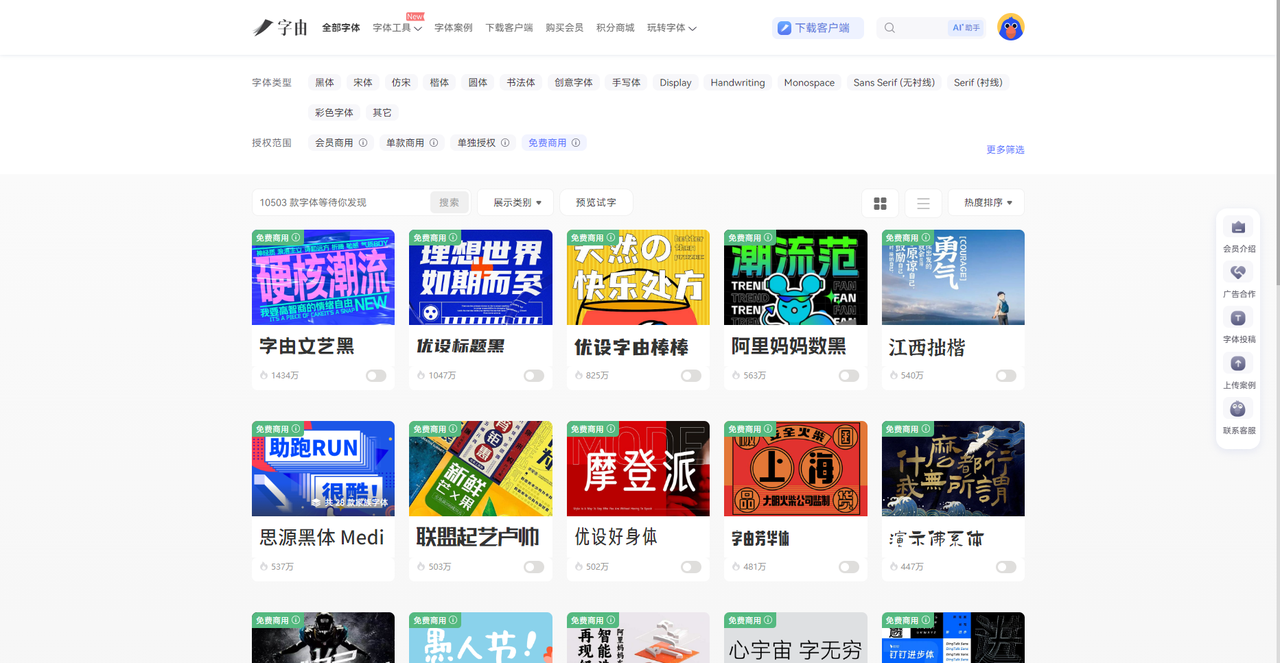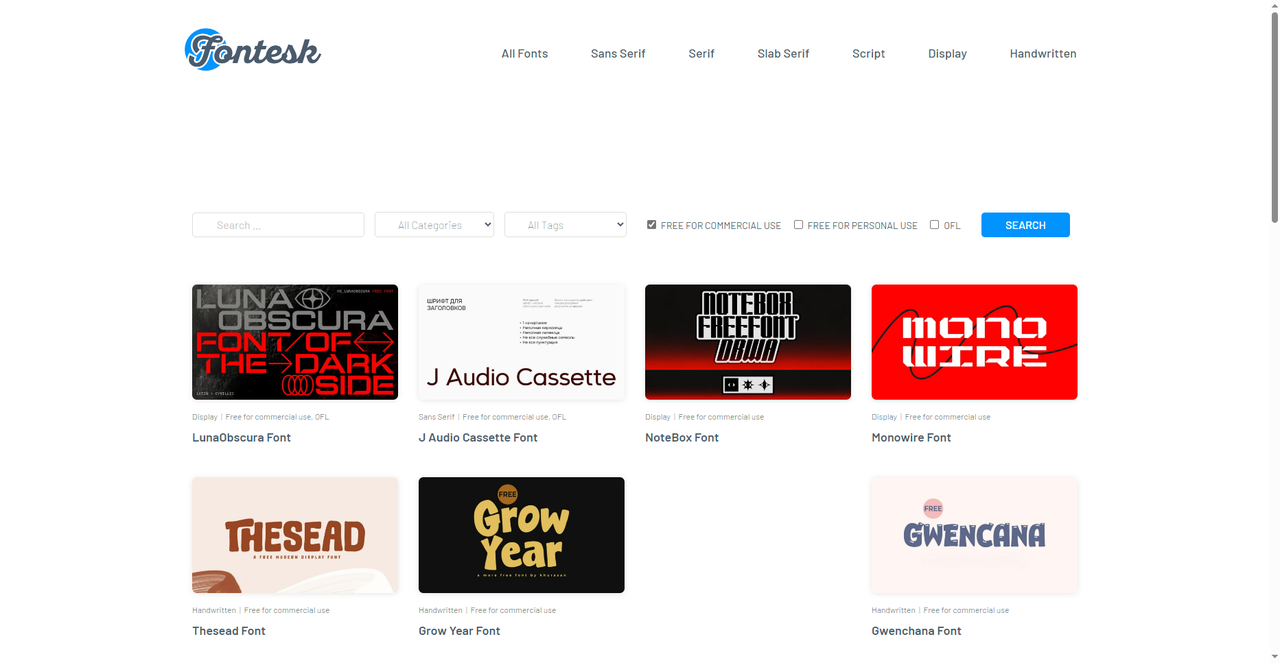
设计师必备!5个可免费商用字体下载网站推荐
每次做设计,总有一瞬间特别纠结:字体选好了,心里却打鼓——这字体到底能不能商用?要不要再查一遍?查吧,怕麻烦;不查吧,又怕出事。最后往往还是妥协,换回系统自带的那几款。明明有那么多好看的字体,就因为“不确定”,不敢用。后来我才发现,其实不是没有好字体,而是没找对地方。那么今天我就会把一些能够明确可以免费商用的字体网站分享给大家,让大家实现用字自由!
很多人用字由,只看到它字体多,却没发现它最好用的是筛选功能。字由收录了超过10500 款字体,其中3585 款是免费可商用的。但如果你不会筛,就会觉得“怎么这么多”。其实掌握下面3 步,你就能在字由里精准定位到想要的那一款。下面我会教大家具体的步骤:
- 第一步:先选授权范围
打开字由客户端或网页版,点进“全部字体”,第一个要看的就是“授权范围”。直接点“免费商用”,系统立刻从一万多款字体里筛出3585款。这个操作帮你排除了所有需要付费或授权不明的字体,剩下的随便用,不用担心侵权。
- 第二步:再筛字体类型
在“字体类型”里,根据你的设计需求选择。做海报标题?点“黑体”或“书法体”。做文艺风?点“手写体”。做UI界面?点“Sans Serif”。这一步帮你把范围从3585款缩小到几百款,更精准。
- 第三步:按风格或热度挑
最后一步,你可以按“字体风格”筛选——想要国潮风点“中国风”,想要可爱点“卡通”,想要高级感点“简约”。或者直接按“热度”排序,优先选使用次数高的,比如“优设标题黑”超1000 万次使用,说明经过了大量设计师的检验。
做完这三步,你就可以从一万多款字体里,精准锁定到几十款既免费商用又符合风格的设计,然后慢慢挑就行。
2、Fontesh
Fontesh 是一个分类非常细致的字体网站,它的“All Tags”里有“FREE FOR COMMERCIAL USE”标签。从主页看,这里收录了多款免费商用字体:
- LunaObscura Font:Display风格,免费商用,OPL授权
- J Audio Cassette Font:Display风格,免费商用
- NoteBox Font:手写风格
- Monowire Font:Display风格,免费商用
- Gwenchana Font:可爱风格
最主要的是每款字体都标注了授权类型和风格标签,方便快速筛选。Fontesh 的分类系统很强大,左侧有Sans Serif、Serif、Slab Serif、Script、Display、Handwritten等大类,每个大类下还有更细的标签。简直不能太好用。
3、Typewolf – Google Fonts精选
Typewolf 是一个专注于字体趋势和推荐的网站,由设计师Jeremiah Shoaf 运营。它有一篇经典文章:“The 40 Best Free Fonts Available on Google Fonts”,最近更新于2026 年1 月12 日。在这里面的40 款字体都是开源免费、可商用的,而且来自知名的字体设计师和代工厂。Typewolf 特意避开了那些只有单字重的展示字体,而是选择了包含多字重、多风格的实用字体家族。每款字体都配有“在真实网站上的应用案例”链接,可以直观感受效果。网站还提供40 款字体的ZIP 打包下载,订阅邮件即可免费获取。
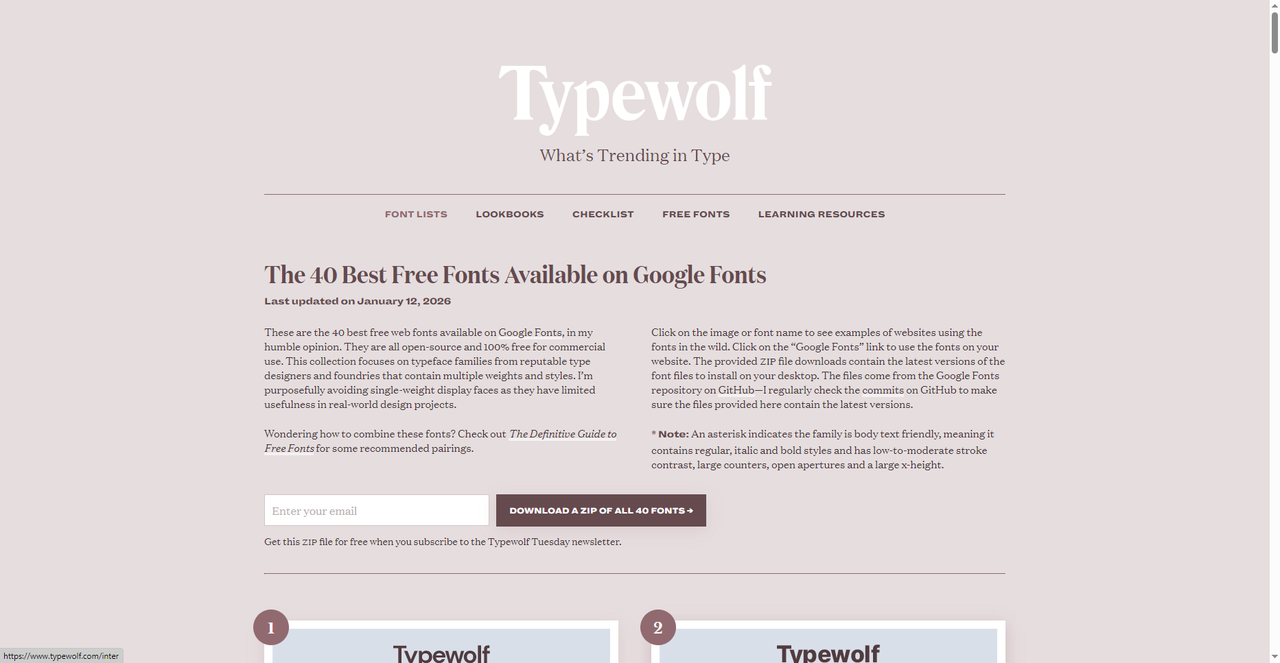
4、1001 fonts
这个网站目前收录了6599款免费商用字体。首页右侧有详细的筛选栏,可以按风格(script、cursive、bold、calligraphy、handwriting),可以快速筛选,每款字体都标注了授权类型,可以按热度、日期、字母顺序排序。网站还支持预览功能,输入你自己的文字,实时看效果。其中我比较推荐的字体有:
- Nerdropol:现代风格
- Holiday Notes Regular:节日主题
- Sparkles And Trippies:装饰性字体
- Quadrillion:多字重字体
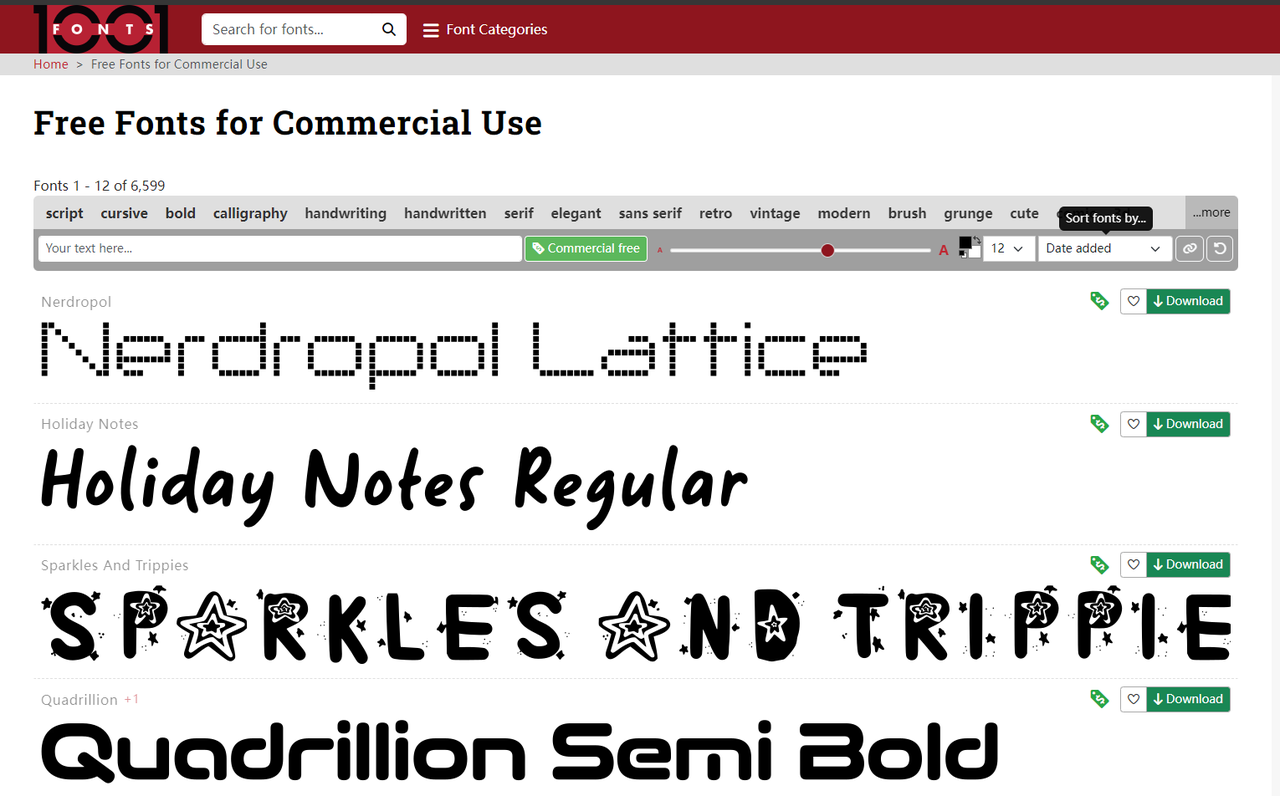
5、FontSpace
这个网站我也经常提到,但是从没有因为免费商用而单独做一次介绍,它的“Commercial-use”分类收录了大量可免费商用字体。首页有“NEW”、“POPULAR”、“RANDOM”、“COMMERCIAL-USE”等分类,方便快速浏览。其中我比较推荐的字体有:
- Super Shiny:由All Super Font设计,100% Free
- Super Adorable:可爱风格,100% Free
- Super Maples:自然风格,100% Free
FontSpace 的优势是社区活跃、更新快,而且每款字体都有下载次数和用户评分,可以帮助你快速判断受欢迎程度。这样的好处就是保证字体库更新速度快,每次用到的时候或许都能有新发现!
以上就是今天要介绍的5 个可免费商用字体下载网站,每一款都提前为你排好了雷。确保你在使用的时候不用再担心版权问题。最主要的是每个网站都十分便捷,下载起来也不需要复杂的操作。但是在这几款里面,字由对我来说是用着最顺手的。因为不仅仅是它有着丰富的免费可商用字体,也因为它能够帮你解决字体方面的其他需求,甚至可以说字由就是一个关于字体的工具箱,如果你也在为字体侵权发愁,不妨从字由开始试试,让设计真正自由。